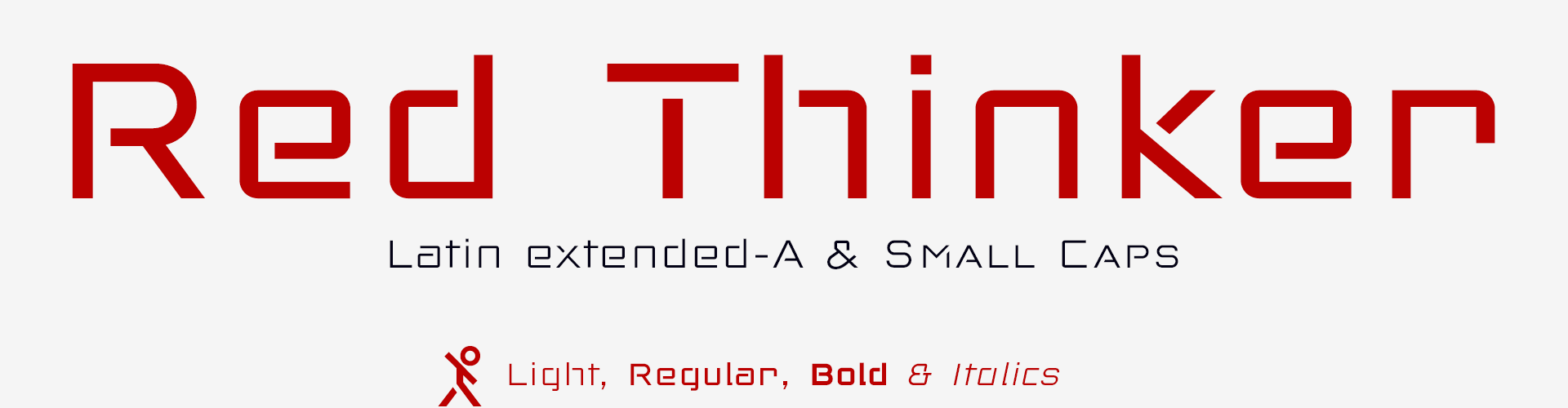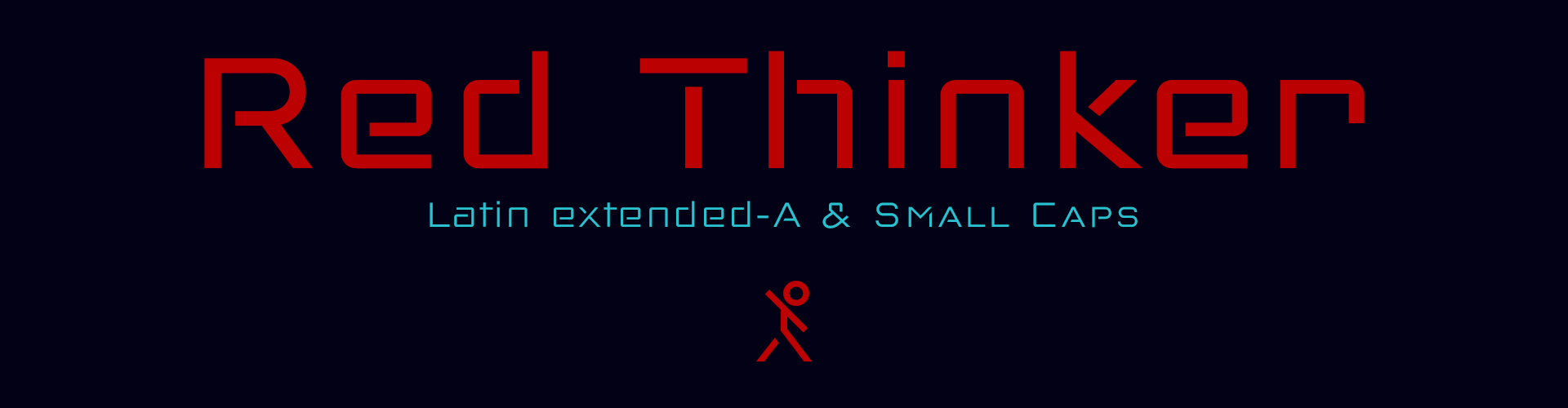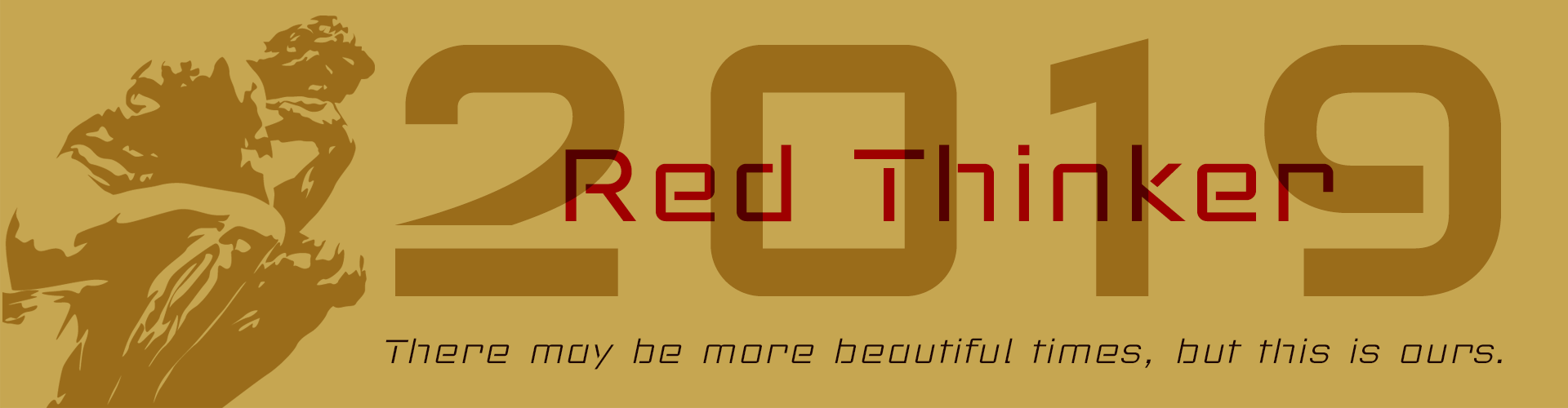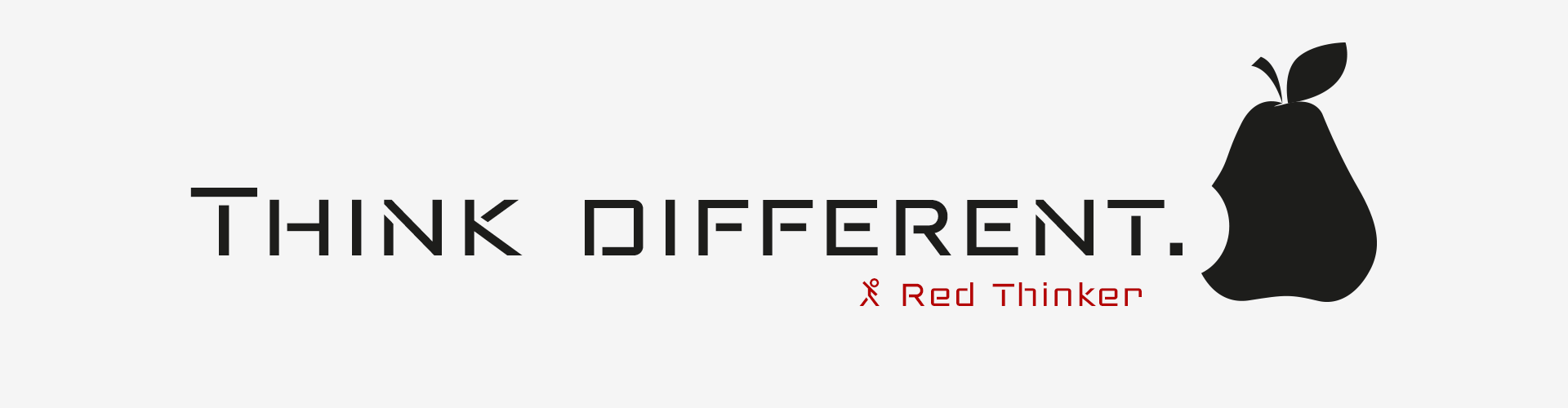
Techno futurist fonts
Estilo: Sans Serif, Stencil, Geometric, Small Caps
Proporción: Light, Regular, Bold & Italics
Glyphs: 810
Alternates: 185
Autor: deFharo
Funciones OpenType: Additional languages, All Alternates, Alternate Annotation Forms, Bitcoin, Capital Spacing, Contextual Alternates, Denominators, Discretionary Ligatures, Extended Fractions, Historical Forms, Inferiors, Kerning, Localized Forms, Numerators, Oldstyle Figures, Ordinals, Scientific Inferiors, Slashed Zero, Small Capitals, Small Capitals From Capitals, Standard Ligatures, Subscript, Superior letters, Superiors, Superscript.
– Red Thinker es heredera por derecho de las fuentes geométricas de principios del sigo XX inspiradas en la escuela Bauhaus y está especialmente diseñada para uso en cualquier tamaño tanto para pantalla como en impresión.
– Red Thinker es una fuente muy versátil para diseño gráfico, podrás usarla en carteles publicitarios, vídeo juegos, títulos de cine, logotipos, diseño editorial, etc.
La fuente «Red Thinker dispone en su versión comercial de un juego de 810 glifos (Latin Extended-A), con soporte para cualquier idioma europeo o centro europeo. Red Thinker también incluye funciones OpenType (Compatibles con InDesign, QuarkXpress, Photoshop e Illustrator.